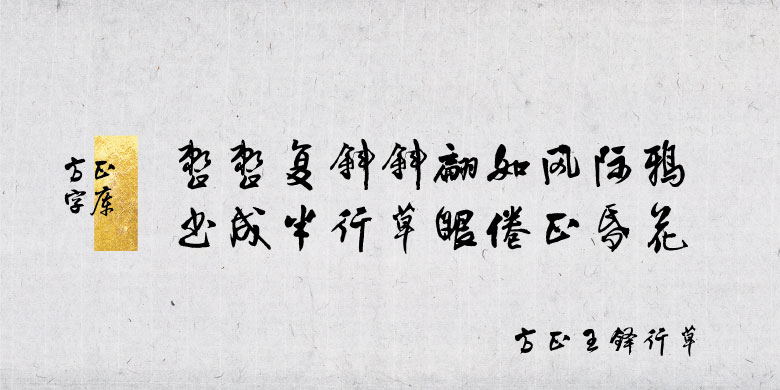
方正王铎行草
品牌:方正字库中华精品字库设计师:禚效锋,杨龙龙发行时间:2019字库编码:大陆简体(GB2312-80)、简繁扩展(GBK)分类:常规书写·毛笔字体属性:精品字
方正王铎行草
王铎(1592-1652),清书法家。字觉斯,号嵩樵,河南孟津人。工行草书,深入阁帖,又得力于颜真卿、米芾二家及历代草法。拓古法而大之,笔力雄健,长于布白,揭开大字行草书的新篇。兼能山水、兰竹。传世墨迹甚多,有《拟山园帖》集刻其法书。
字体特征:以王铎主要传世墨迹为开发依据。运笔酣畅,劲健洒脱,变化多端,仪态万方。